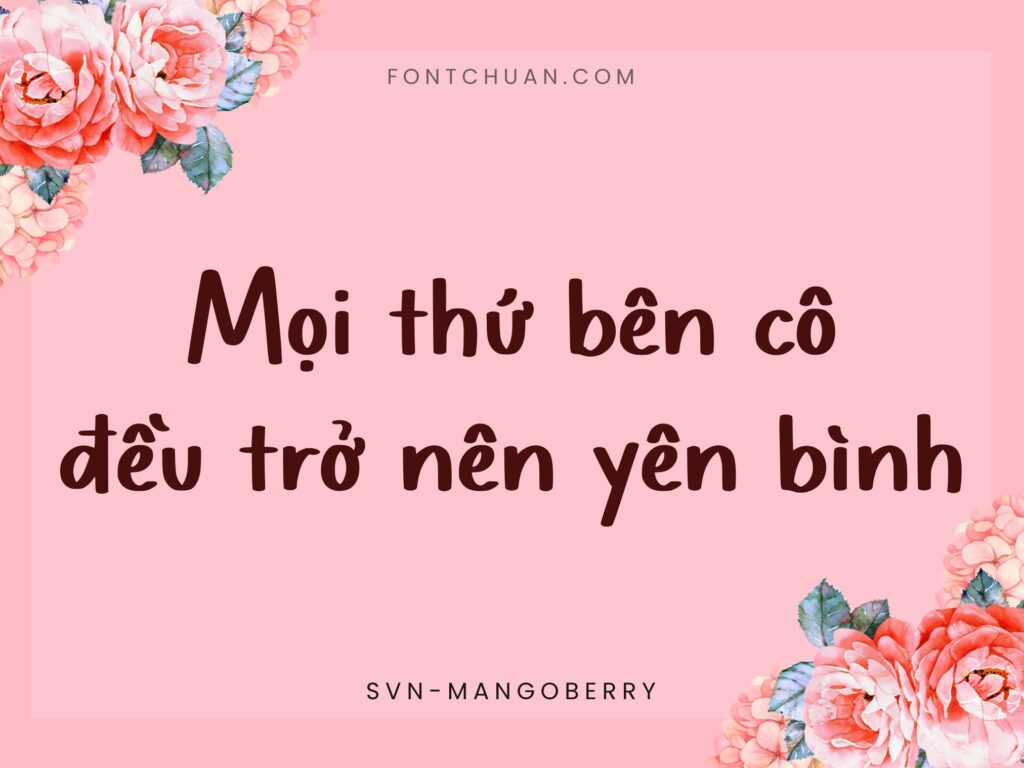
Font SVN Mangoberry Việt Hóa
Tác giả Font: Allouse.Studio
Font SVN Mangoberry là phiên bản Việt hóa của kiểu chữ Mangoberry, được thực hiện bởi STYLEno.1 Fonts. Mangoberry là một kiểu chữ viết tay dễ thương, với các đường nét mềm mại và tròn trịa, mang lại cảm giác thân thiện và gần gũi. Font này bao gồm đầy đủ các ký tự chữ hoa, chữ thường, chữ số và dấu câu, hỗ trợ đa ngôn ngữ. Mangoberry phù hợp cho nhiều mục đích sử dụng như thiết kế tiêu đề, logo, bao bì sản phẩm và các ấn phẩm truyền thông.
SVN Mangoberry lý tưởng cho các dự án thiết kế yêu cầu sự vui tươi và thân thiện, như thiết kế tiêu đề, logo thương hiệu và các ấn phẩm truyền thông. Các ngành nghề như giáo dục, ẩm thực và thiệp cưới có thể tận dụng font này để tạo điểm nhấn trong thiết kế. Ngoài ra, font cũng thích hợp cho các sự kiện như Tết, Giáng sinh, Halloween và các lễ hội khác.